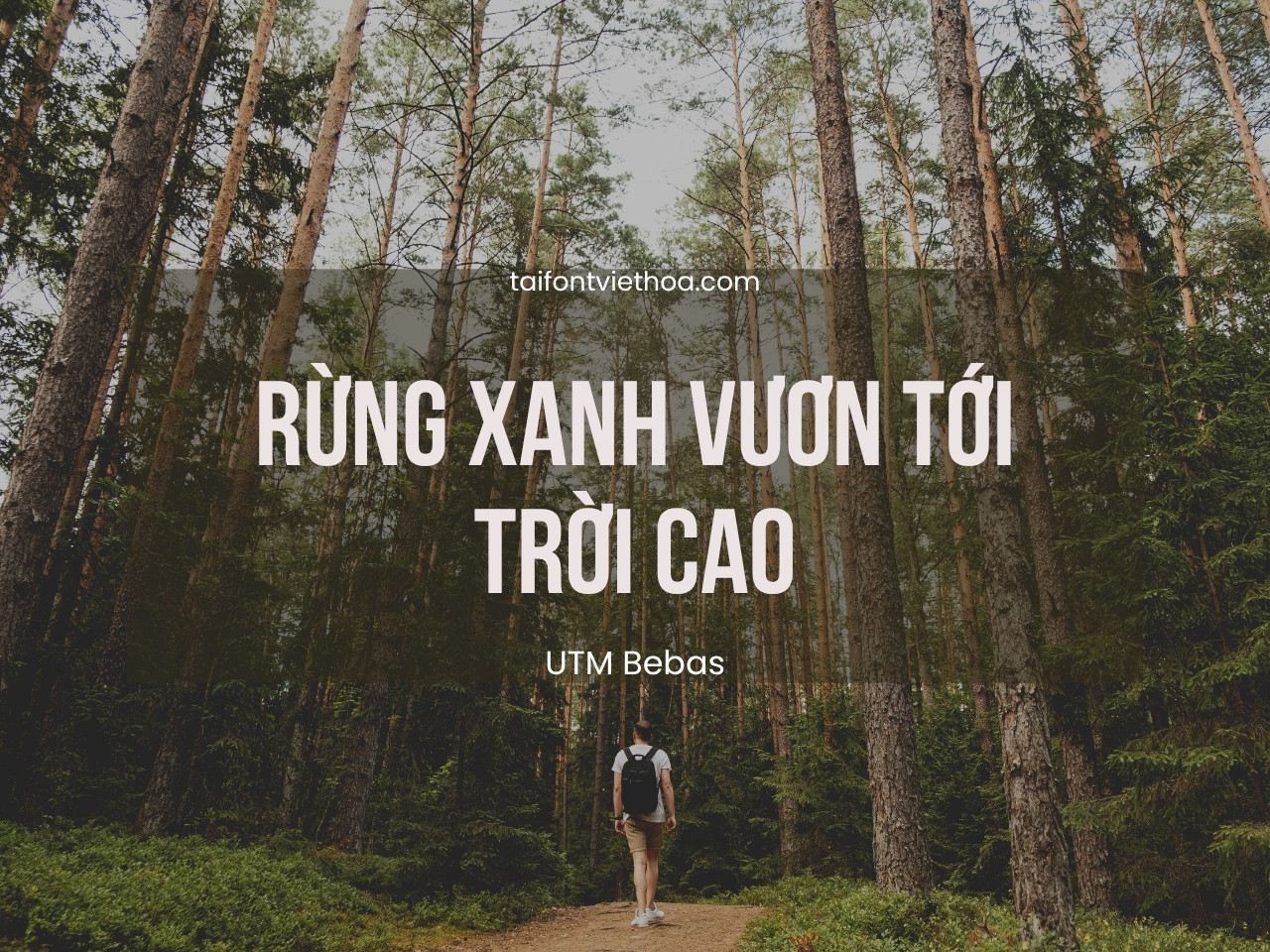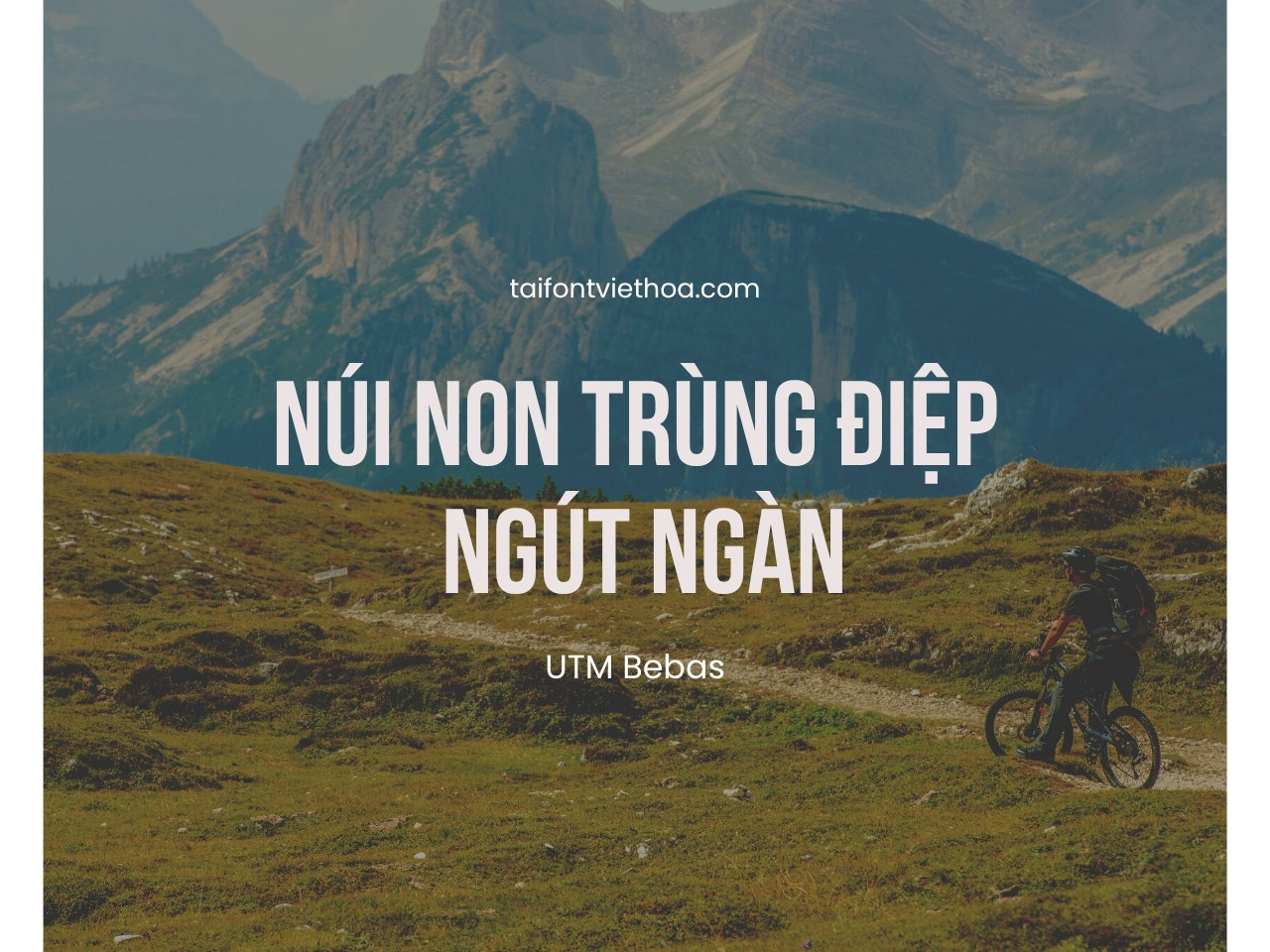
Font việt hóa UTM Bebas
Giới thiệu về font UTM Bebas
UTM Bebas là phiên bản Việt hóa của font Bebas – một kiểu chữ sans-serif đậm nét, nổi bật và hiện đại, được thiết kế bởi nhà thiết kế Ryoichi Tsunekawa. Font gốc Bebas nổi tiếng với sự khỏe khoắn, các ký tự viết hoa đồng đều và dễ đọc, rất được ưa chuộng trong các thiết kế quảng cáo, poster và tiêu đề. Phiên bản Việt hóa đã được hoàn thiện để hỗ trợ đầy đủ tiếng Việt và hơn 200 ngôn ngữ khác, mở rộng khả năng ứng dụng trong các dự án sáng tạo đa dạng.
Đặc điểm thiết kế và ứng dụng của UTM Bebas
UTM Bebas sở hữu cấu trúc sans-serif không chân với các nét chữ đậm, vuông vức và rõ ràng. Font có thiết kế đơn giản, hiện đại, tạo hiệu ứng thị giác mạnh mẽ và dễ nhận biết, rất thích hợp cho tiêu đề, logo, bảng hiệu và các ứng dụng quảng cáo khác. Font còn được cân chỉnh tối ưu để đảm bảo sự hài hòa và dễ đọc trên nhiều kích thước và bối cảnh sử dụng.
Font phù hợp sử dụng trong các dự án thiết kế logo, nhận diện thương hiệu, quảng cáo, bảng hiệu và truyền thông đa phương tiện. Các ngành nghề phù hợp gồm: quảng cáo, công nghệ, thể thao, thời trang và truyền thông sáng tạo.